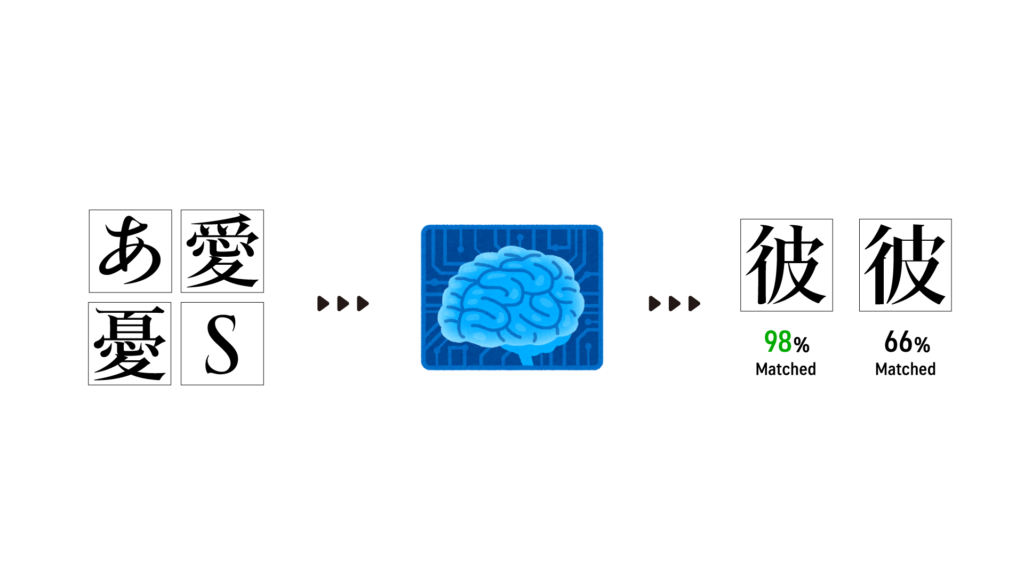
機械学習と書体03「機械学習を用いた書体の品質保証」
書体デザインの品質保証を行うのに、人によるチェックだけではなく、機械学習を用いたチェックが行えると考えられています。一貫した書体を持つ文字は、全ての文字で共通の「書体特徴」を持っていると考えられます。その書体特徴を機械学習によって見つけ出し、デザインチェックに用いることで機械的に一定の品質を保てるようになります。
この手法が確立すると、複数人のデザイナーによってデザインされた文字でも一貫された書体を保つようにチェックが行えるようになります。また、一つの文字に複数のデザイン案があった時に、機械的にどちらがよりマッチした文字かを選択することができるようになります。
機械学習と書体の組み合わせは今回紹介したもの以外にも、カーニングや組版に活用するものなどがあり、広い範囲で活用されていくであろう技術なので、今後も注目の内容です。